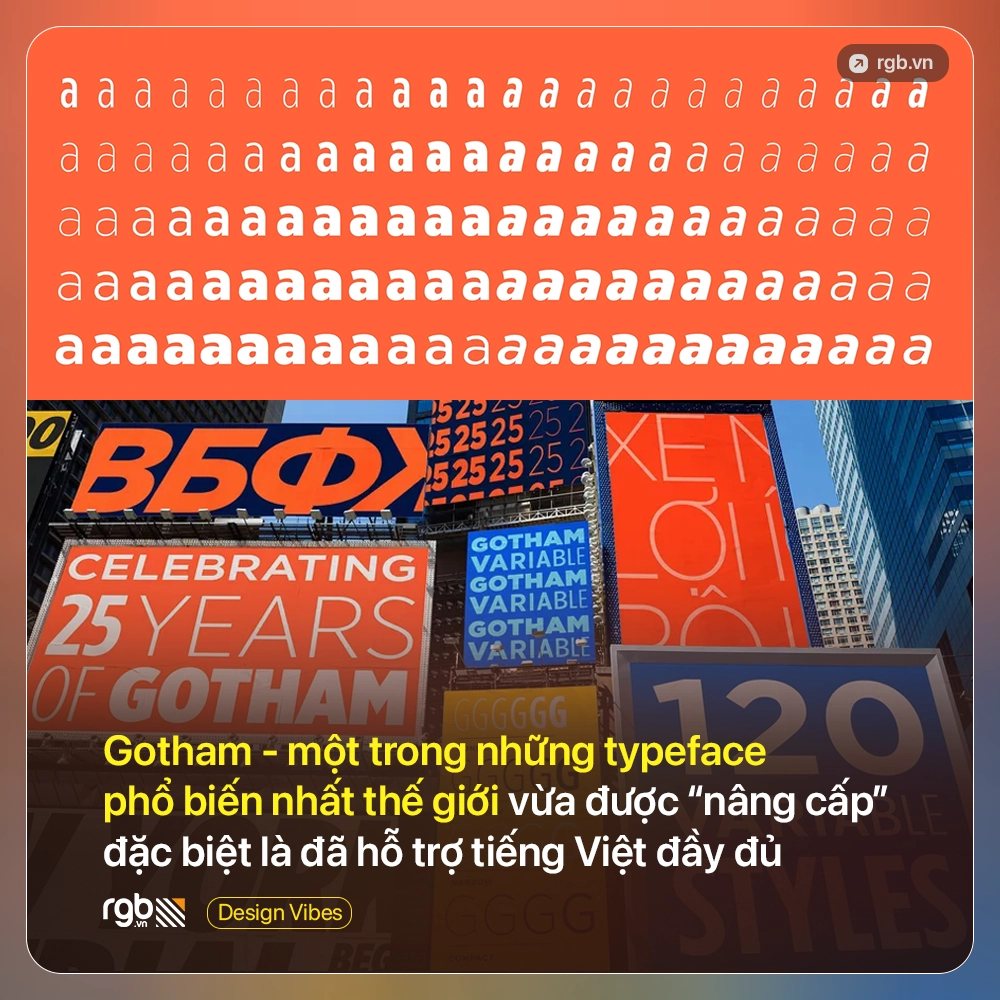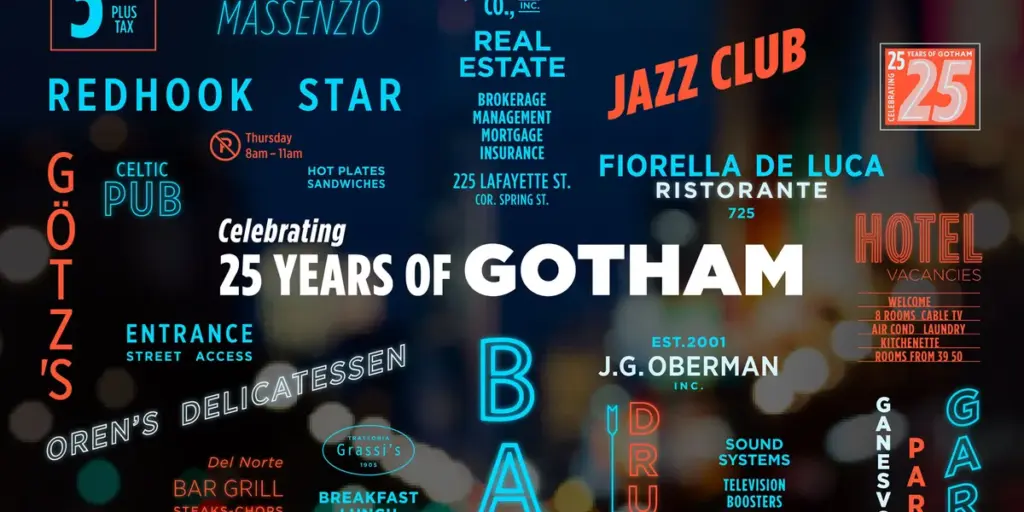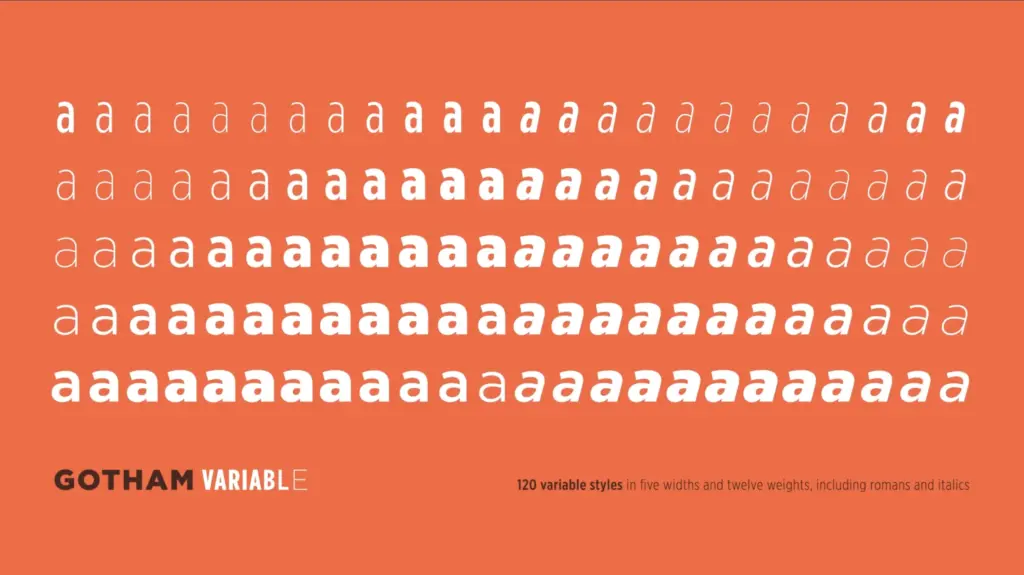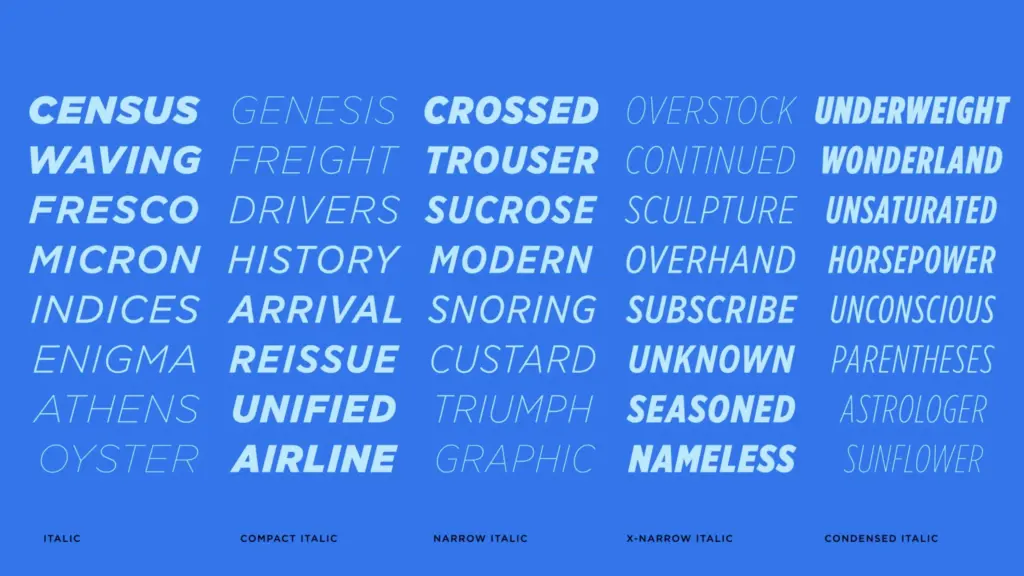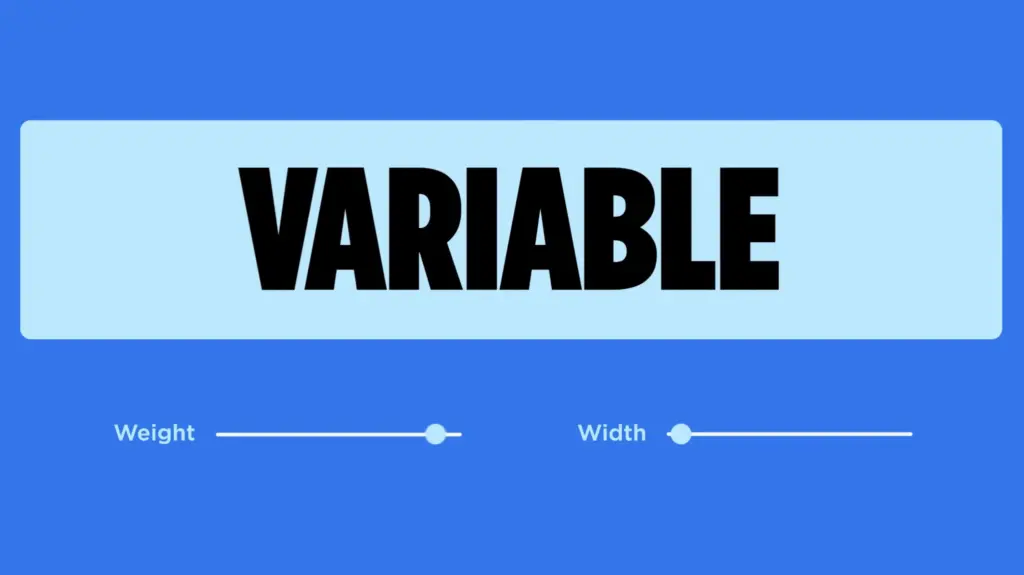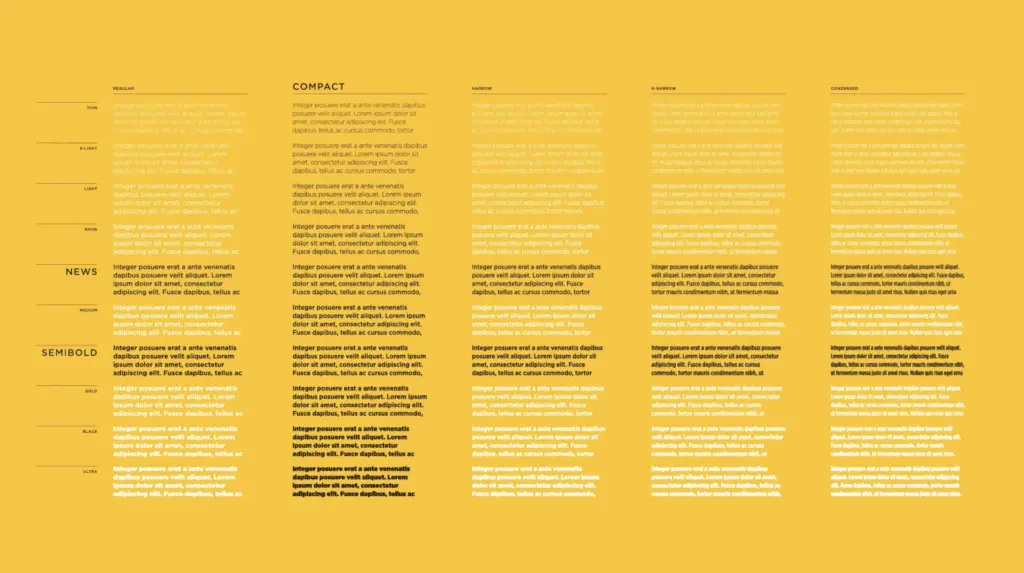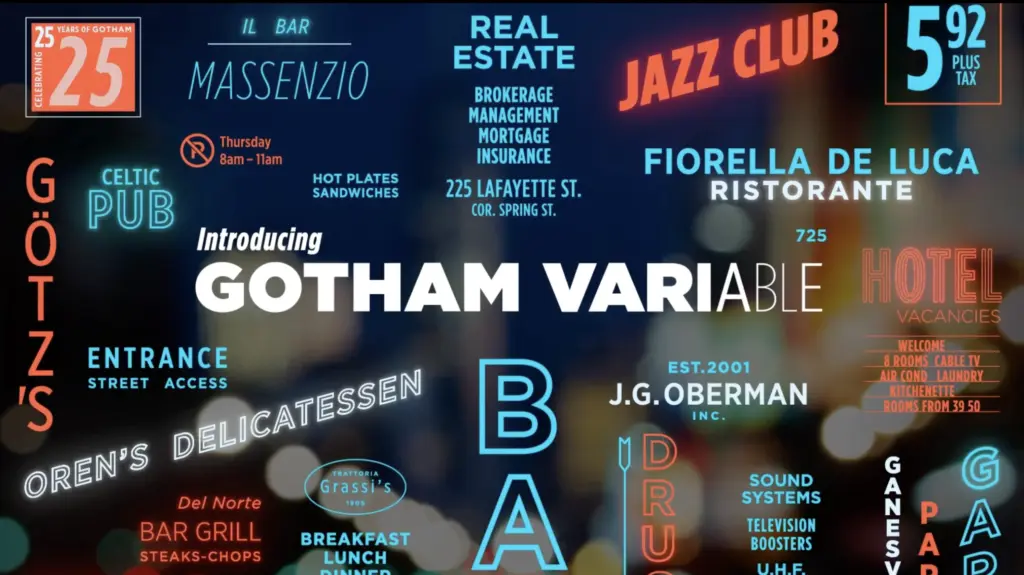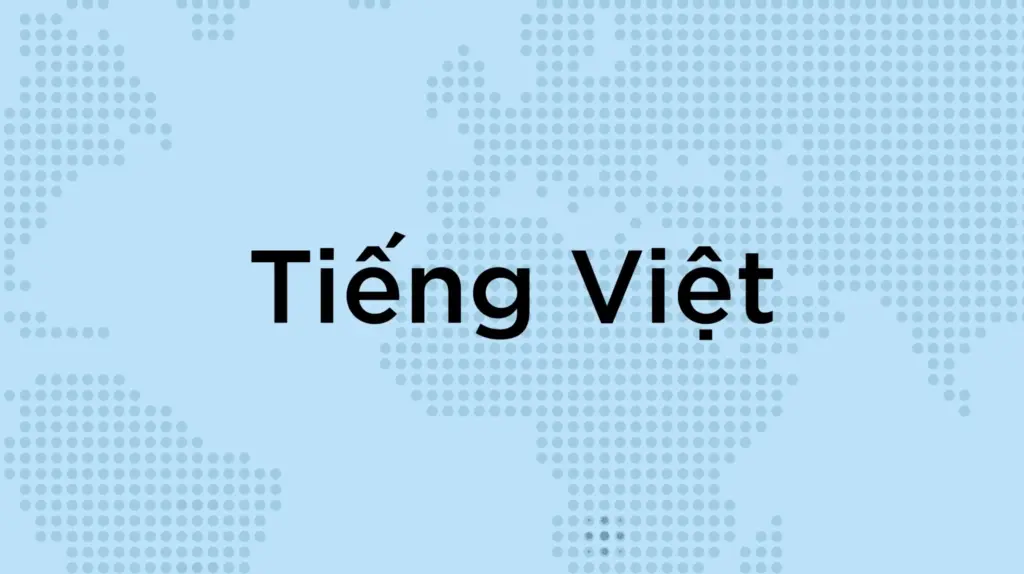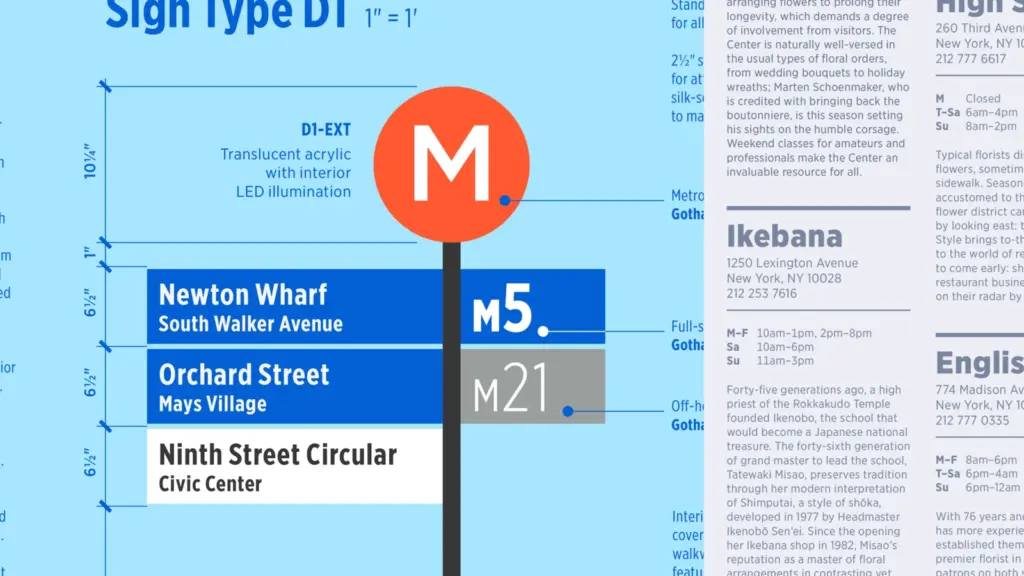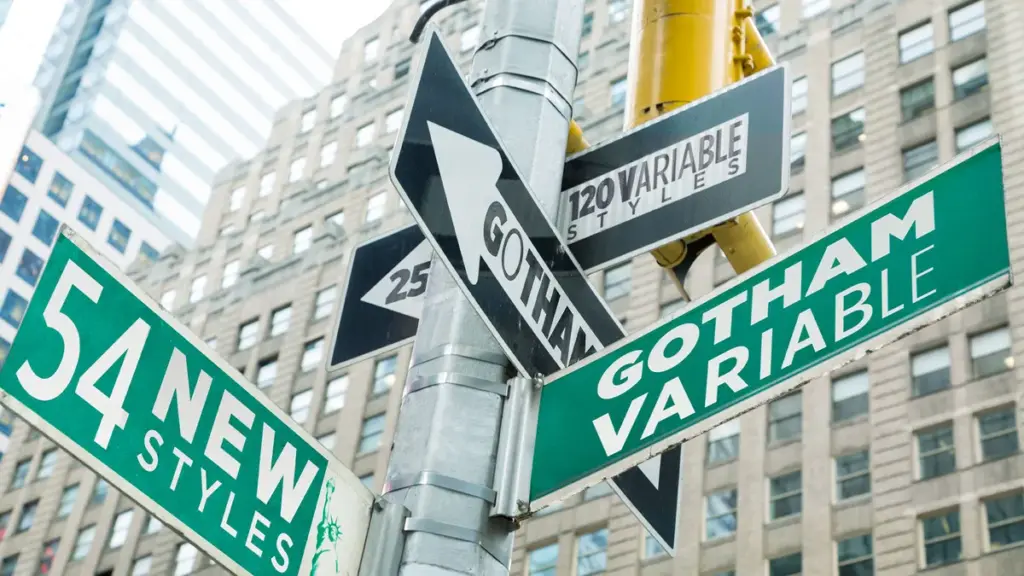
Gotham – một trong những font chữ nổi tiếng và được sử dụng nhiều nhất thế giới vừa được Monotype nâng cấp lên phiên bản mới mang tên Gotham Variable. Đây được xem là bước tiến lớn của typeface biểu tượng này, khi lần đầu cho phép designer điều chỉnh liên tục độ đậm (weight) và độ rộng chữ (width) chỉ trong một file duy nhất đã được tối ưu hiệu năng.
Được thiết kế bởi Jonathan Hoefler và Tobias Frere-Jones, rồi phát hành bởi Hoefler & Co., Font Gotham lần đầu xuất hiện công khai trên bìa tạp chí GQ vào tháng 1/2001 trước khi nhanh chóng trở thành một trong những typeface mang tính “default của văn hóa đại chúng”.
Suốt hơn 25 năm qua, Gotham xuất hiện khắp nơi: từ Netflix, Coca-Cola cho tới USPS hay chương trình Saturday Night Live và đặc biệt nổi tiếng nhờ chiến dịch tranh cử của Barack Obama.
Giờ đây, Gotham bước sang một giai đoạn mới với khả năng thích ứng linh hoạt hơn nhiều cho môi trường digital hiện đại. Thay vì phải dùng hàng chục file static riêng biệt, Gotham Variable gom toàn bộ vào một file duy nhất, giúp giảm thời gian load, cải thiện performance, đơn giản hóa việc triển khai trên nhiều nền tảng, đồng thời cho phép designer tinh chỉnh typography mượt hơn rất nhiều. Phiên bản mới cũng bổ sung thêm 54 style trung gian hoàn toàn mới, bao gồm nhiều mức weight tinh tế hơn và cả width “Compact” mới.
Một trong những nâng cấp đáng chú ý nhất với designer Việt Nam là Gotham Variable giờ đã hỗ trợ tiếng Việt đầy đủ, bao gồm các dấu phức tạp, stacked accents và tone marks. Typeface cũng được mở rộng hỗ trợ cho Cyrillic và Bulgarian. Jordan Bell – Senior Type Designer tại Monotype cho biết việc thêm language support vào một typeface có sẵn chưa bao giờ là chuyện đơn giản: “Đặc biệt với các chi tiết như hook và horn trong tiếng Việt, điều quan trọng là phải giữ được đúng tinh thần thị giác vốn có của Gotham.”
Theo Sara Soskolne – Executive Creative Director tại Monotype và lead designer của Gotham Variablecho, thử thách lớn nhất của dự án nằm ở việc thêm variable functionality và hỗ trợ tiếng Việt mà không phá vỡ cấu trúc vốn đã rất quen thuộc của Gotham. “Trước đây, các khoảng chuyển giữa những static styles là nơi chúng tôi ‘giấu kỹ thuật’ để mọi thứ trông đúng như ý muốn. Nhưng khi chuyển sang variable font, toàn bộ khoảng chuyển đó giờ đều hiển thị hoàn toàn với người dùng,” bà nói. Với tiếng Việt, thử thách còn khó hơn vì stacked accents cần thêm không gian chiều dọc, trong khi team không muốn thay đổi line-height đặc trưng của Gotham.
Một điều thú vị khác là dù có cơ hội “mở nắp capo” và chỉnh sửa nhiều quyết định thiết kế cũ, team cuối cùng vẫn quyết định không biến dự án thành “Gotham 2.0”. Thay vào đó, họ giữ khả năng backwards compatibility hoàn toàn, chỉ mở rộng thêm những gì người dùng có thể làm mà không thay đổi DNA nguyên bản của typeface.